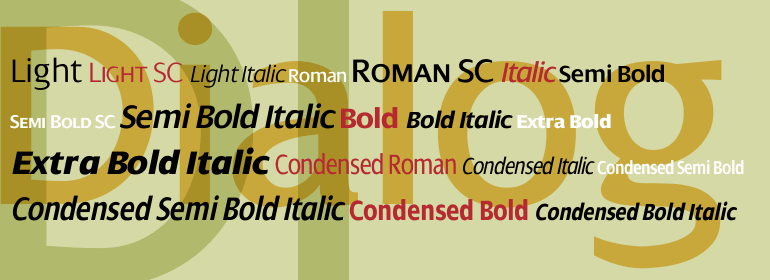
Dialog™
Dialog™,这款字体结构工整、笔画清晰,兼顾美观与易读性,适用于标题、正文、海报、包装、LOGO 等多种场景。字形优雅稳定,风格百搭耐看,适配日常排版与创意设计,让文字呈现更舒适、更具质感。Dialog™一笔一画,皆是细节,以均衡的比例、流畅的线条打造舒适视觉体验,字形端正大气,风格简约现代。无论是商业设计、品牌宣传还是日常排版,都能轻松驾驭,让文字更有格调与力量。Dialog™字体下载。
“Dialog是作者设计的第一款无衬线字体。我早些时候做过一些尝试,但他们满足不了我的需求。相反,Dialog非常鼓舞人心,我制作了19种不同的字体,这是几年来最完整的字体。我通常更喜欢带有衬线的字体,但我不会在Dialog中使用。”
Dialog于1993年发布。
Dialog is my first sans serif. I had made some attempts earlier, but they didn't satisfy me. Dialog was, on the contrary, so inspiring that I made 19 different fonts of it, the most complete typeface for several years. I usually prefer typefaces with serifs, but I don't miss them in Dialog. The name needs no explanation.
Dialog was released in 1993.